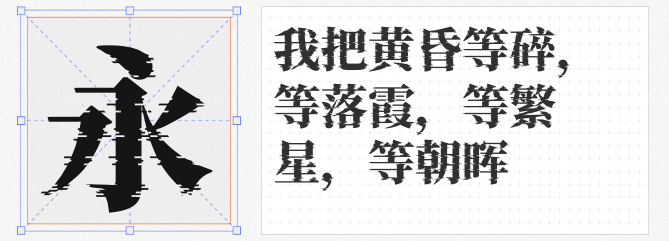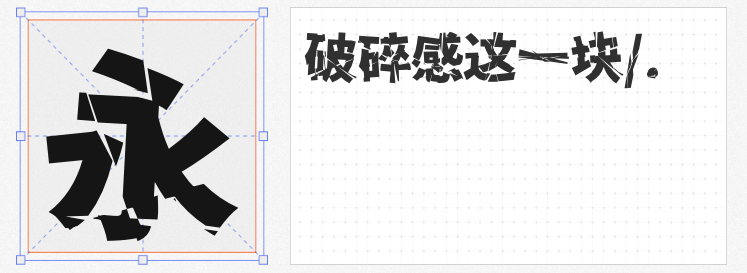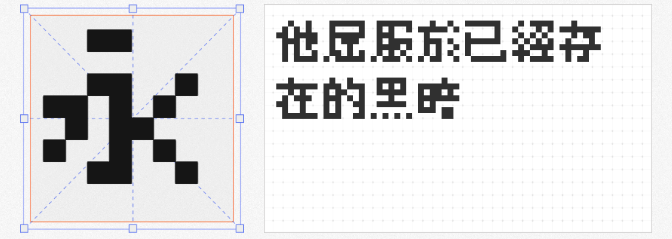
在追求视觉冲击力的酷炫风格设计中,字体是塑造氛围、传递态度的关键元素。一款个性鲜明的字体,能让作品瞬间脱颖而出。以下四款免费商用字体,以独特的倾斜角度、像素颗粒感、故障特效和几何切割,为电竞、游戏、潮牌等场景注入强烈态度,设计师可放心用于商业项目。
1. 斗鱼追光体2.0
作为斗鱼直播平台的定制字体,斗鱼追光体2.0以向右8°的倾斜角度打破常规,暗喻电竞“向前冲刺”的竞技精神。这种斜体设计自带动态感,仿佛每个字符都在奔跑中捕捉光芒。字体巧妙融合传统书法笔锋——藏锋的含蓄与露锋的锐利交织,既保留书写韵律,又赋予科技感的速度表达。无论是电竞海报的标题,还是动态视频的字幕,斗鱼追光体2.0都能用倾斜的姿态传递“追逐热爱”的品牌内核。
2. 精品点阵体7×7
基于美咲フォント改作的点阵体,以7×7的像素方块重构汉字,每个字符都像从8位游戏机中跃出。颗粒感十足的笔画,搭配方正的像素结构,瞬间唤醒复古游戏情怀。这款字体特别适合像素风海报、游戏UI或潮牌T恤设计,用低分辨率的粗糙质感碰撞现代设计,营造出“刻意做旧”的潮流态度。
3. 猫啃网故障宋
继承思源宋体CN的完整字符,猫啃网故障宋通过算法模拟数据错乱的视觉效果——笔画扭曲、色彩叠加、边缘破碎,仿佛字符正在经历一场数字故障。尽管程序生成导致部分字形不够完美,但这种“不完美”恰恰成为赛博朋克风格的标志。适用于科技产品海报、音乐节视觉或未来感主题包装,用故障特效传递叛逆与未知。
4. 香萃零度黑
源自日文字体【零ゴシック】的简化版本,香萃零度黑以强烈的几何切割重塑汉字结构。笔画被刻意扭曲、撕裂,形成尖锐的棱角与不规则的空白,营造出暗黑、前卫的视觉冲击。这款字体适合潮牌LOGO、金属乐队海报或极限运动宣传,用“破坏感”的设计语言诠释个性与反叛。
四款字体,四种酷炫表达——斜体的速度感、像素的复古感、故障的未来感、切割的暗黑感,为设计师提供丰富的创意弹药。免费商用的属性,更让创意无后顾之忧。